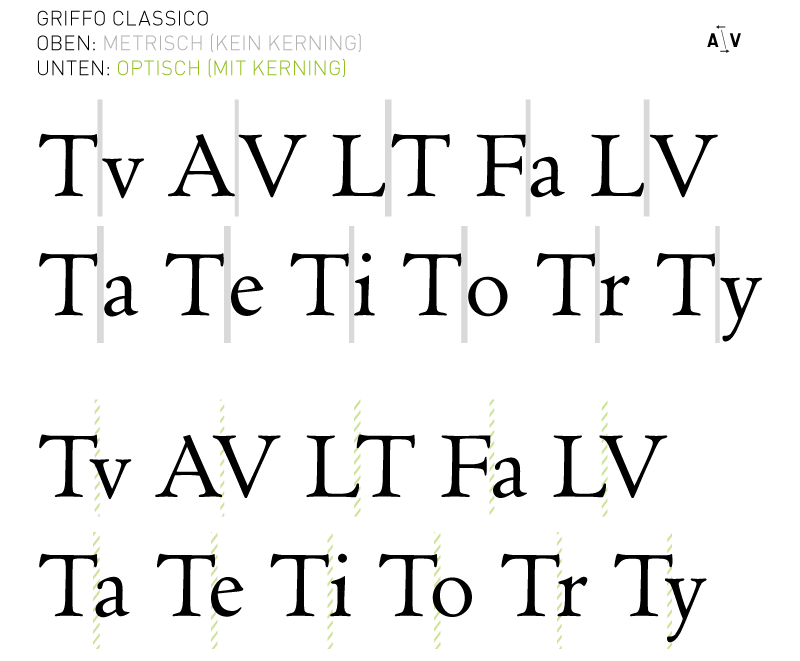
„Typographischer Terminus aus dem englischsprachigen Raum für das Ausmitteln kritischer Buchstabenkombinationen; ästhetischer Schriftweitenausgleich kritischer Buchstabenpaare innerhalb eines Fonts, der in einer Unterschneidungs-, Ästhetik- oder Kerning-Tabelle durch den Schriftgestalter vorgegeben wird. In der Mikrotypographie auch als ‚Zurichtung einer Schrift‘ bezeichnet. Automatisches Ausmitteln bezeichnet man besser als ‚Kerning‘, manuelles Ausmitteln als ‚Ausgleichen‘ (Optischer Schriftweitenausgleich).“ (Quelle: Typolexikon Beinert).
Kerning ist das englische Pendant zum deutschen »Unterschneiden«. In der Zeit des Bleisatzes wurden die nichtdruckenden Teile zwischen den beiden Zeichen weggeschnitten, wodurch der Abstand enger wurde.
Wieso ist das Kerning so wichtig? Aus einer gut gekernten Schrift ergeben sich die gute Lesbarkeit und harmonische Textkomposition.
Nur der Satz, in dem die Buchstaben rhythmisch gleichlaufend stehen, erfüllt die erste und wichtigste Forderung, nämlich ‚ohne Mühe, ohne Umwege und ohne den Lesefluss hemmende unnötige Verzierungen dem Leser das gesprochene Wort wiederzugeben‘ (Hermann Zapf). Der Gleichlauf des Textes bedeutet die geringste Mühe für den Leser. Verständlicherweise sind die Unterschneidungswerte für eine große Display-Schrift mit beispielsweise Buchstabengrößen bis 50 cm anders als die Werte für die gleiche Schrift als Bodytext in einer Zeitschrift. Alle Schriften in den URW-Bibliotheken werden im Hinblick auf ihr Haupteinsatzgebiet für einen bestimmten Größenbereich optimiert. Die Zeichenabstände der Textschriften werden größer gehalten als die der Displayschriften. Ein anderer wesentlicher Unterschied betrifft das Design der Schriftzeichen. Vor allem die Schriften mit einem hohen Fett/Feinkontrast und entsprechend dünnen Haarlinien und Serifen erfordern spezielle Textversionen. Die Haarlinien und Serifen werden in solchen Fällen kräftiger gestaltet als in der entsprechenden Displayvariante. Ist der Fett/Feinkontrast gering, wie bei Grotesk- und Egyptienneschriften, werden andersartige Anpassungen vorgenommen. In kleineren Schriftgraden laufen bei solchen Schriften die spitzen Winkel zu. Um diesem Effekt optisch entgegenzuwirken, werden die Schriftzeichen an solchen Stellen mit feinen Einzügen versehen (Mittag O., Typografie und die URW DeSign Collection, Auszug aus „PrePress“ Nr. 4/1995, 7).
Viele Schriften werden heute aufgrund mangelnder finanzieller Ressourcen schlecht bzw. überhaupt nicht gekernt. In einem hochwertigen Font kann es hingegen bis zu 80.000 Kerningpaare geben. Die URW Schriften beispielsweise enthielten nicht selten an die 1000 gekernte Buchstabenkombinationen. Das speziell für das Kerning entwickelte Programm „Kernus“ sorgte für die automatische Berechnung, die sorgfältig überprüft und gegebenenfalls manuell nachbearbeitet wurde. Diese Vorgänge hatten Einfluss auf die hohe Qualität der Schrift, wirkten sich allerdings auch auf den Preis der einzelnen Fontfamilien aus.
URW führte in die Schriftwelt auch jene Abkürzungen zu den Namen der jeweiligen Schrift ein, die den optimalen Einsatzgebiet der Schrift bezeichneten:
| T | Text (je nach Ausgabegerät von 6 pt bis 18 pt) |
| D | Display (ab 18 pt) |
| L | Laserdrucker |
| M | Monospaced (gleiche Zeichenbreite bei allen Buchstaben des Alphabets) |
| E | Extreme (besonders schmale, extra große, extra weite bzw. enge Schriften) |
| P | Poster (extrem große Schriften) |
Hinweis: für besondere Zwecke – wie beispielsweise das Telefonbuch, Tabellen und Zifferreihen – gibt es auch Schriftarten ohne Unterschneidung wie Courier, Bell Centennial, Letter Gothic, Monaco u. a.
Typische Kerningpaare:
|
AV AvAwAy |
aj av aw ay |